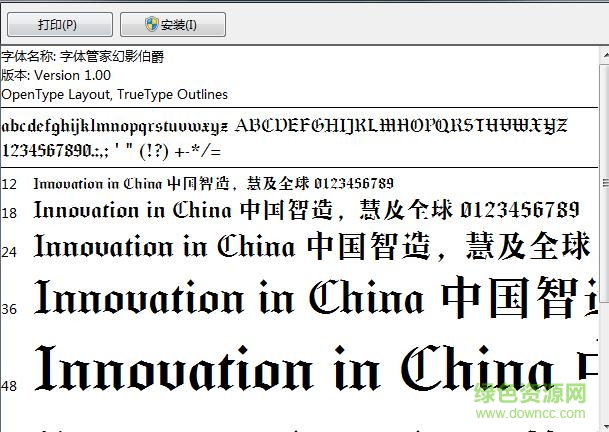
字體管家幻影伯爵體
幻影伯爵字體是一款具有西方中世紀風格的手寫字體,該字體整體看上去非常的醒目,并且不論是漢字還是英文,都有非常鮮明的特點,有需要可以下載使用!
幻影伯爵字體簡介
幻影伯爵字體是字體管家打造的一款西方特色的中文字體,具有西方手寫字的特色,你可以將其用于海報設計、雜志設計、涂鴉設計等方面。
幻影伯爵字體